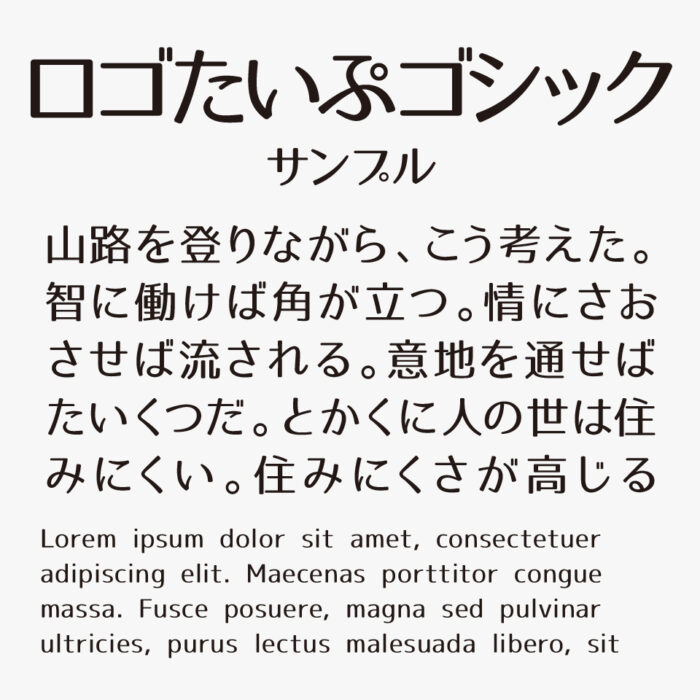
ロゴたいぷゴシックフォントは、ロゴデザインやタイトルロゴ、見出しなどに向いている漢字も含まれる日本語フリーフォントになります。
一般的なゴシックとは少し違い、文字の先端が先細っているのでタイポス系の表情を持っている特徴的のフォントです。
ロゴたいぷゴシック
スマートでかっこいいジ印象になるので、ビジネスなどのロゴに向いているフォントです。ベタ打ちしただけでもロゴのようになるディティールなども細かく非常に整っているフォントです。
収録文字は、数字、アルファベット、記号、かな文字(ひらがな・かたかな)、教育漢字、常用漢字、第一水準漢字、第二水準漢字(途中まで完成)、その他主要な多言語が収録されているので、幅広いジャンルで使うことができます。